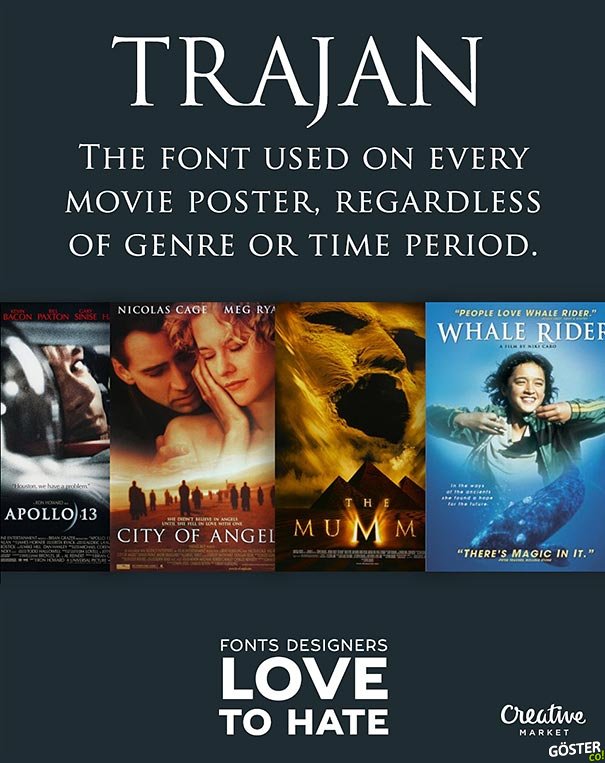
İnsanların Nefret Etmekten Keyif Aldığı 11 Yazı Tipi
Trajan: Tüm film afişlerinde, filmin türü fark etmeksizin, umarsızca kullanılan artık gına gelmiş font.